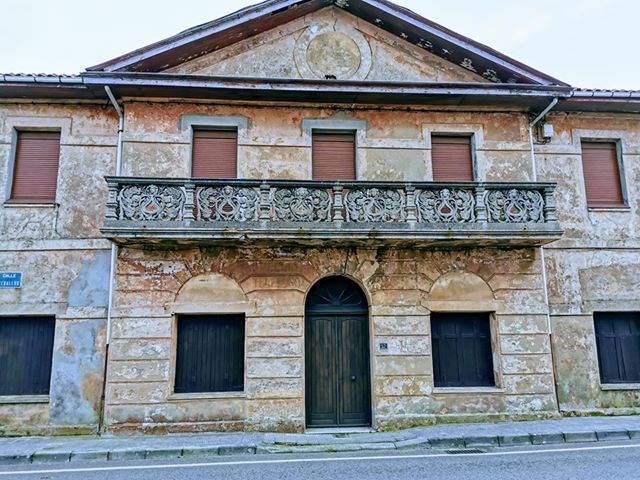
Aureliano Sandi (Suances)
Francisco Javier Iturri Rozadilla manda estas fotos desde Suances para saber que es lo que pone, ya que le llamó la atención. En ellas se ve que en la fachada hay una rotulación con una tipografía modernista y lo que pone es «Aureliano» «Teléfono».
Tras sacar estos datos, Francisco tiró del hilo y descubrió que se trata de una tienda que se la conocía como «El Paraiso». Más adelante era alquilado como alojamiento para los veraneantes. Esta tienda Fue abierta por Aureliano Sandi, un veterano comerciante que ya tenía un Ultramarino con el mismo nombre en Torrelavega en 1908 tal y como figura en un directorio comercial de dicho año.